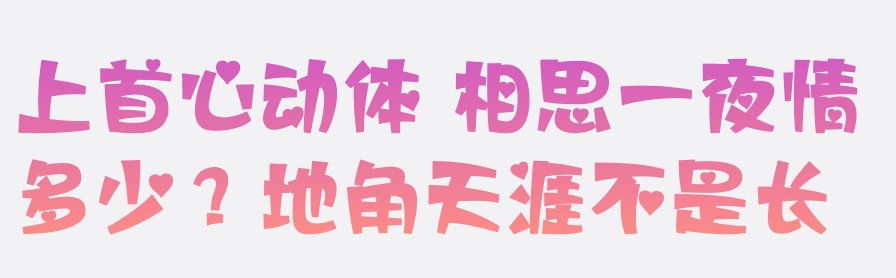
上首心动体--可商用的甜蜜爱心字体
《上首心动体》最大特点就是它的灵动俏皮。每一个笔画仿佛都蕴含着一种欢快的情感,就像两颗心在跳跃,每一次的碰撞都充满了活力。字体的线条流畅而柔和,令人联想到恋人之间轻轻的触碰。
除了俏皮的感觉,字体中还融入了爱心的元素。每一个笔画之间都似乎隐藏着一个小小的爱心,仿佛在默默地诉说着爱情的故事。这种甜蜜的元素让整体风格既奇妙又令人陶醉,就像恋爱中的美好瞬间一样。
如果你想要在设计中传达浪漫和甜蜜,不妨考虑使用《上首心动体》这个字体。它将为你的作品注入一股爱的氛围,让观者感受到那份特殊的心动和甜蜜。无论是制作卡片、海报还是情书,这个字体都能让你的设计更具情感和吸引力。